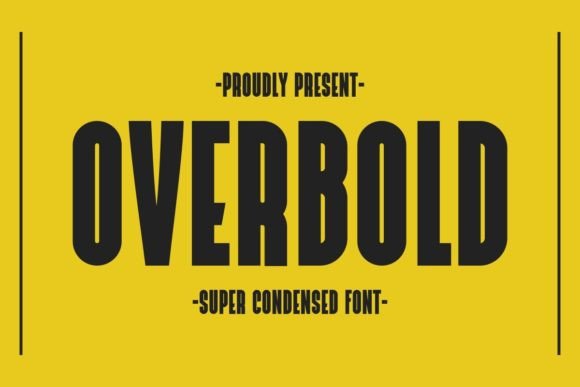
Overbold
การค้นหาองค์ประกอบการออกแบบที่เหมาะสมอาจเป็นเรื่องท้าทาย แต่ Overbold นำเสนอคอลเลกชันที่โดดเด่นซึ่งช่วยยกระดับงานของคุณได้ทันที
ไม่ว่าคุณจะสร้างผลิตภัณฑ์ POD (Print on Demand) คำเชิญงานแต่งงาน หรือกราฟิกโซเชียลมีเดีย Overbold ก็เหมาะสมอย่างยิ่ง